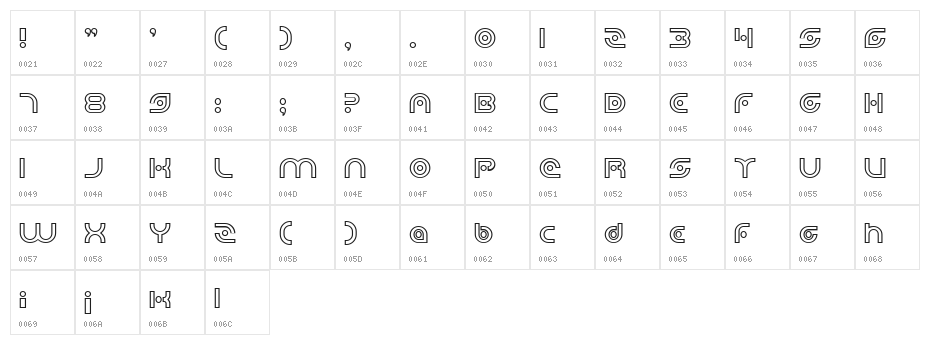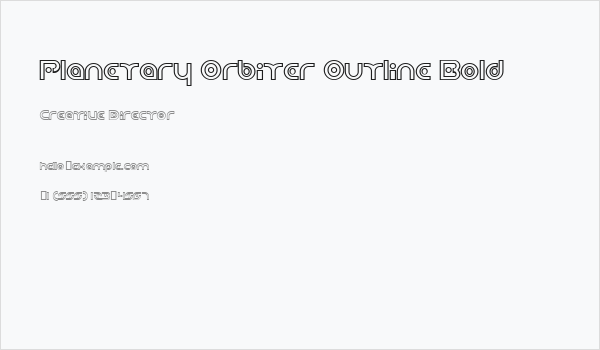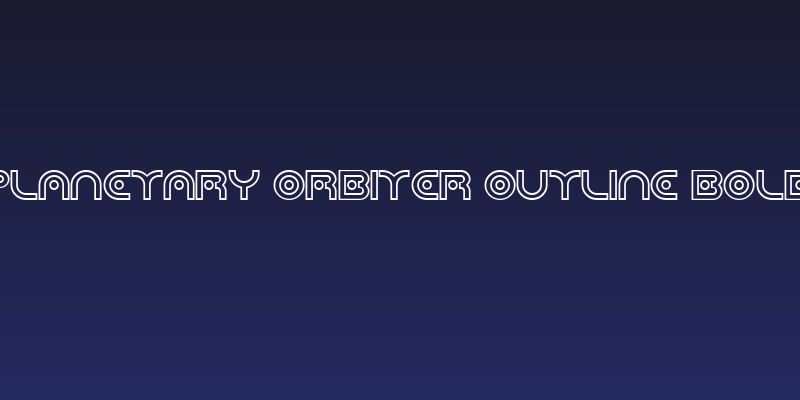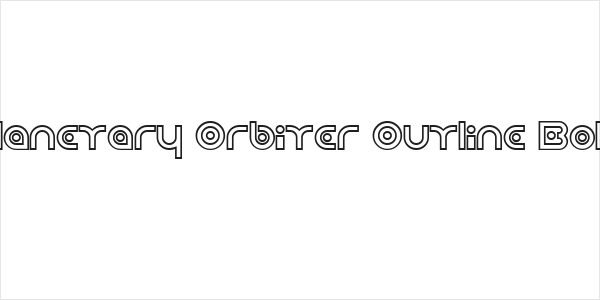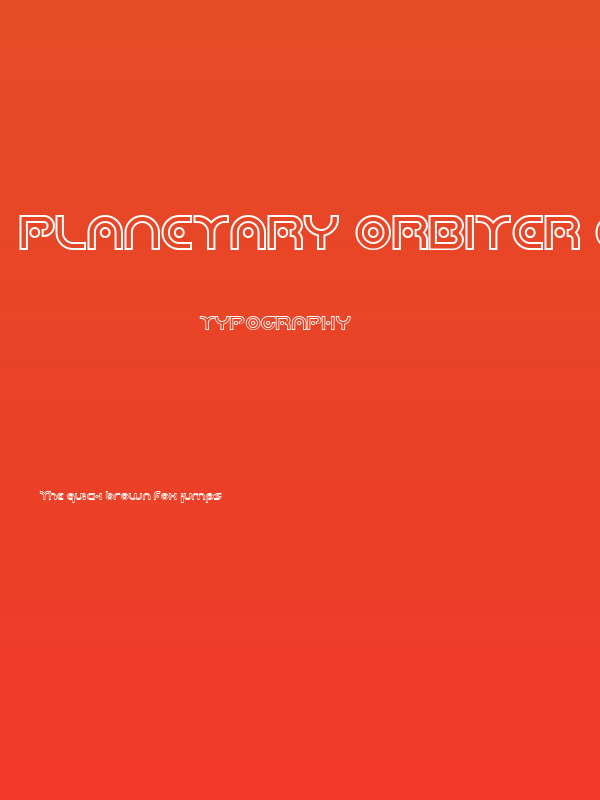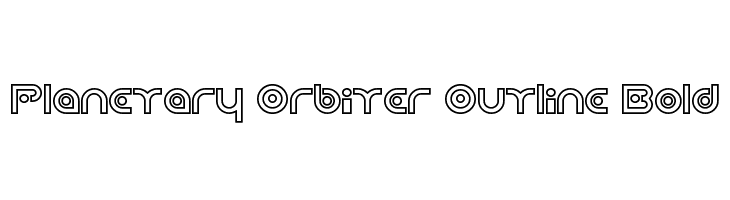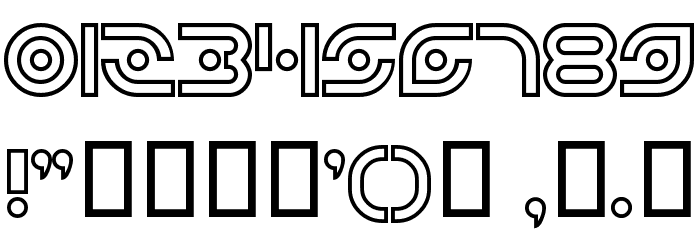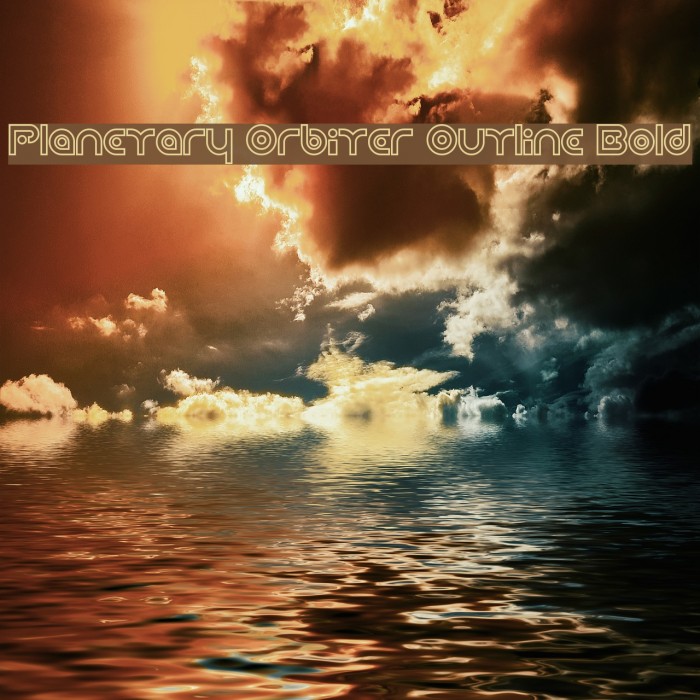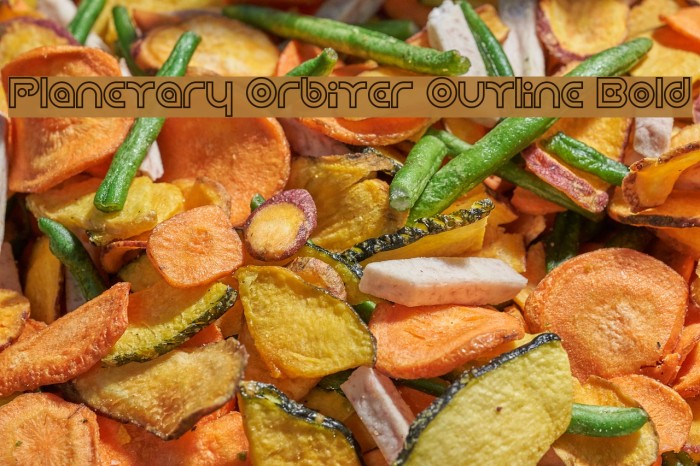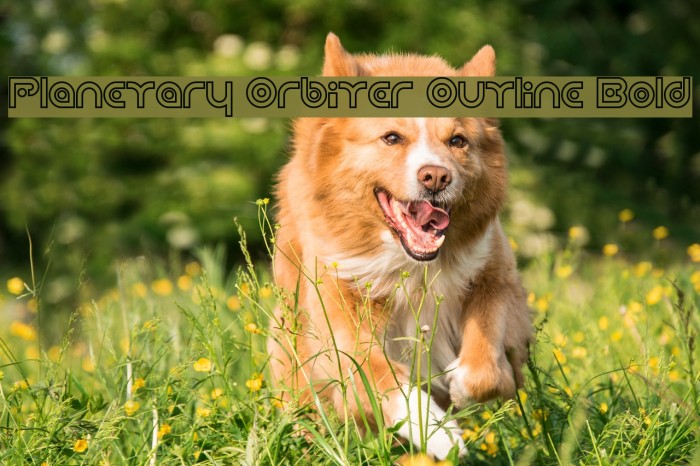
Planetary Orbiter Outline Bold Font
| Nom | Planetary Orbiter Outline Bold |
| Poids | Bold |
| Projets proposés | Ideal for sci-fi themed designs, technology branding, video game titles, and futuristic posters. |